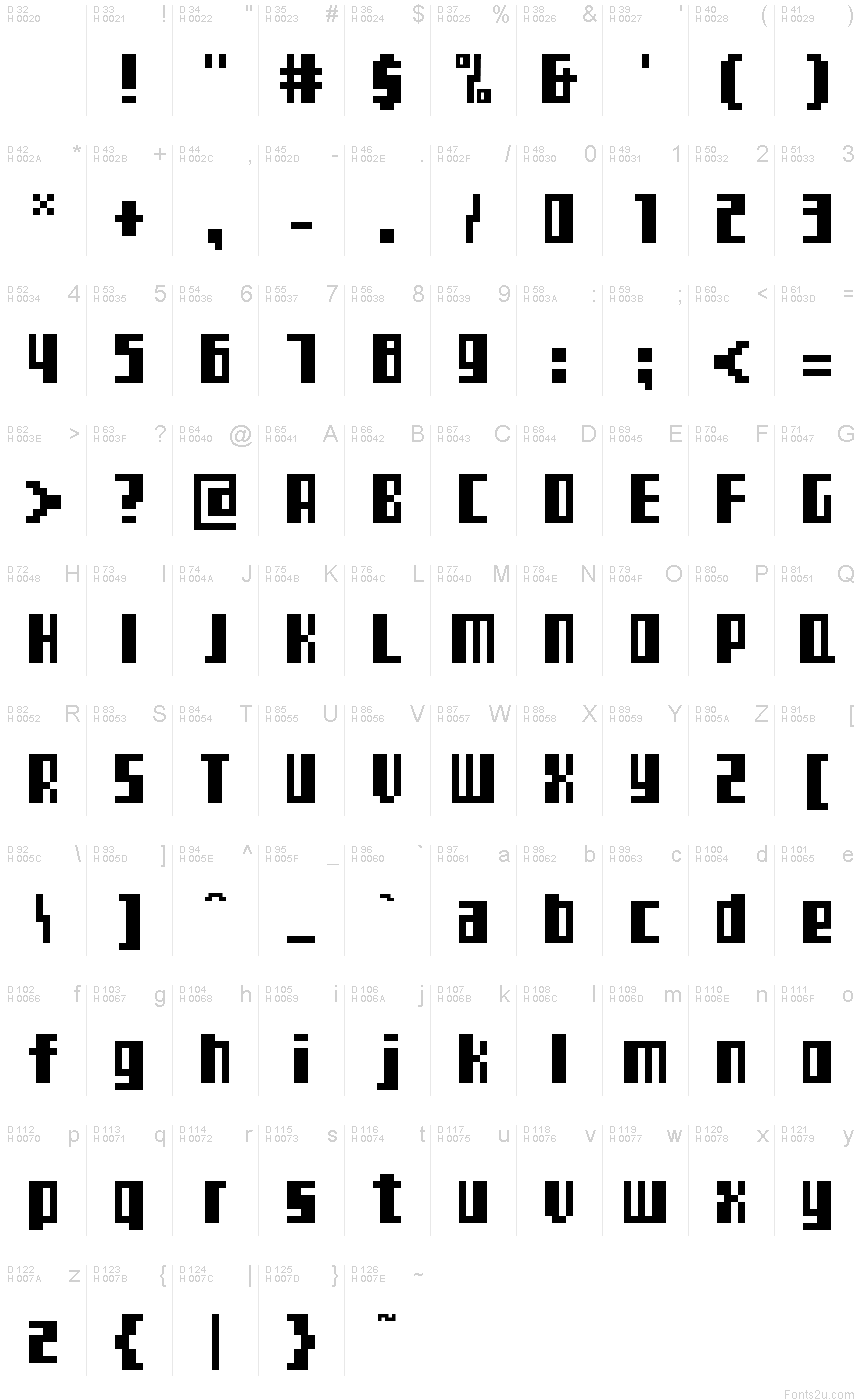
TeleTekst
TeleTekst من LeFly هو خط نقطي (Bitmap) مجاني يتمتع بجاذبية شاشات العرض القديمة. الحروف مبنية من كتل مربعة كبيرة وفراغات ضيقة، مما يمنح الخط إيقاعاً خشناً وعالي الوضوح يشعرك وكأنه مقتبس من صفحات "التليتيكست"، والواجهات القديمة، ورسومات الألعاب الكلاسيكية.
وهذا يجعل من TeleTekst خياراً طبيعياً لملصقات الريترو، وعناوين المجلات، ونماذج واجهات المستخدم، وعناوين الألعاب، والرسومات الويب السريعة التي تحتاج فيها إلى خط مجاني يتميز بنسيج البكسل الواضح لإنجاز العمل بسرعة. كما أنه مناسب لعناوين الأغلفة والشعارات المختصرة، لأن أشكاله المربعة الثقيلة تحافظ على مظهر ثابت ومنضبط للعبارات القصيرة.